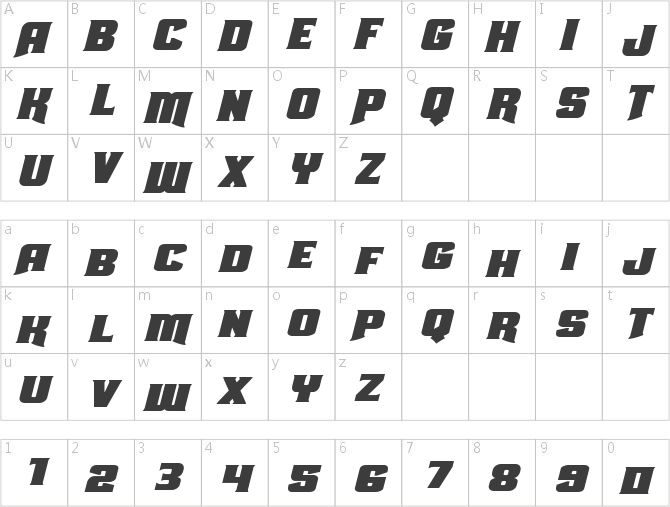
Union Gray Expanded Italic
Union Gray Expanded Italic介绍
Union Gray Expanded Italic字体字库是一款让人赏心悦目、百看不厌的英文字体,适合各类广告和产品包装设计应用,字体大小0.04MB,格式为ttf字体,上传用户是KISEKI,作者/版权方为未知